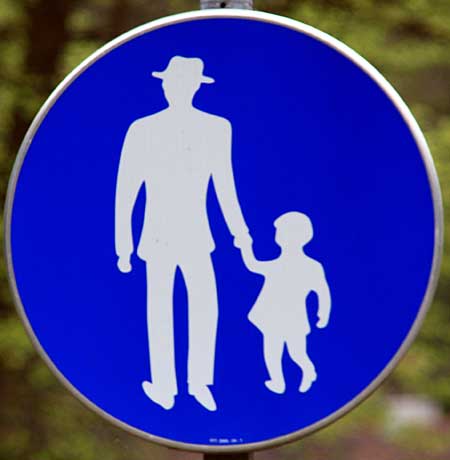
Der Krieg um die Zeichen
Sind die verschiedenen Rettungswege-Männchen jetzt gedacht, um Männer und Frauen (oder langhaarige oder gar schon brennende) zu einem anderen Rettungsweg zu schicken, durfen dann Rettungswege mit männlichem Symbol nur noch von ordentlich frisierten Männern genutzt werden?
Irgendwie ist das doch Kontraproduktiv.
Da fehlt ganz eindeutig noch ein Fluchtweg für intersexuelle farbige Transgender, die lesen können und sich durch solche Schilder für stinknormale, aber möglicherweise analphabetische Weiße (!) natürlich diskriminiert fühlen müssen und deshalb wohl im Brandfall jämmerlich ersticken ...
Nun ja, ein Schild, das es in Österreich noch gibt, hatten wir einst in sehr ähnlicher Gestaltung auch in Deutschland (Fassung vom 29. März 1956). Dies wurde damals recht heftig diskutiert. Ich erinnere noch in Hamburg die Bezeichnung als "Mitschnacker-Schild"